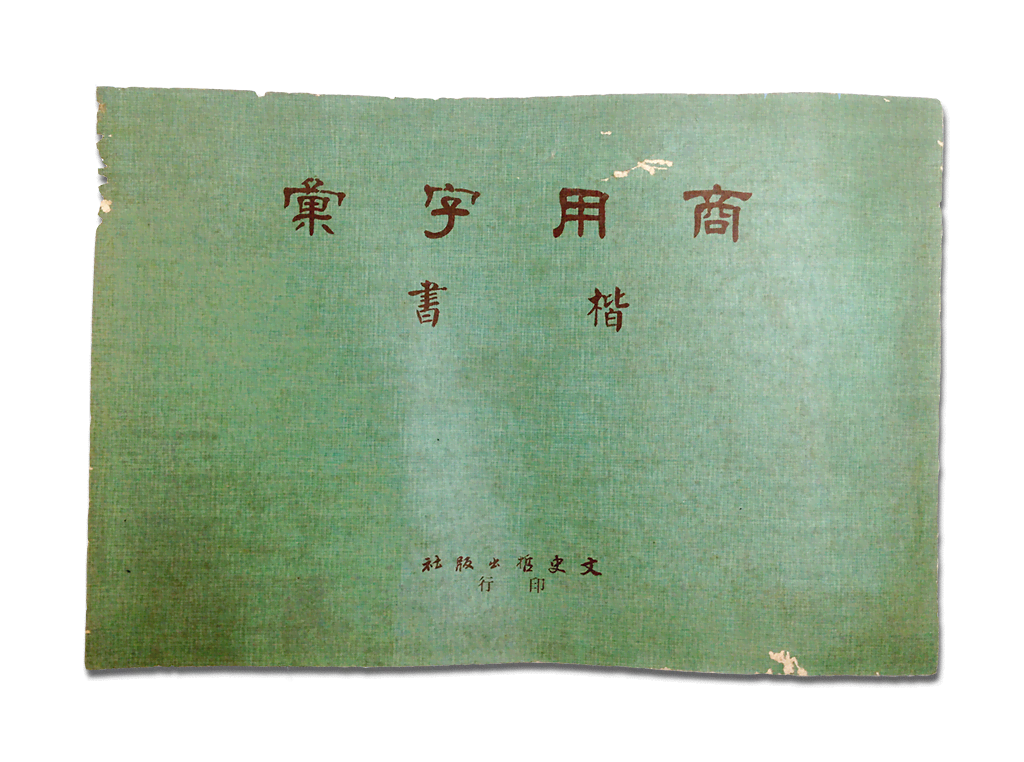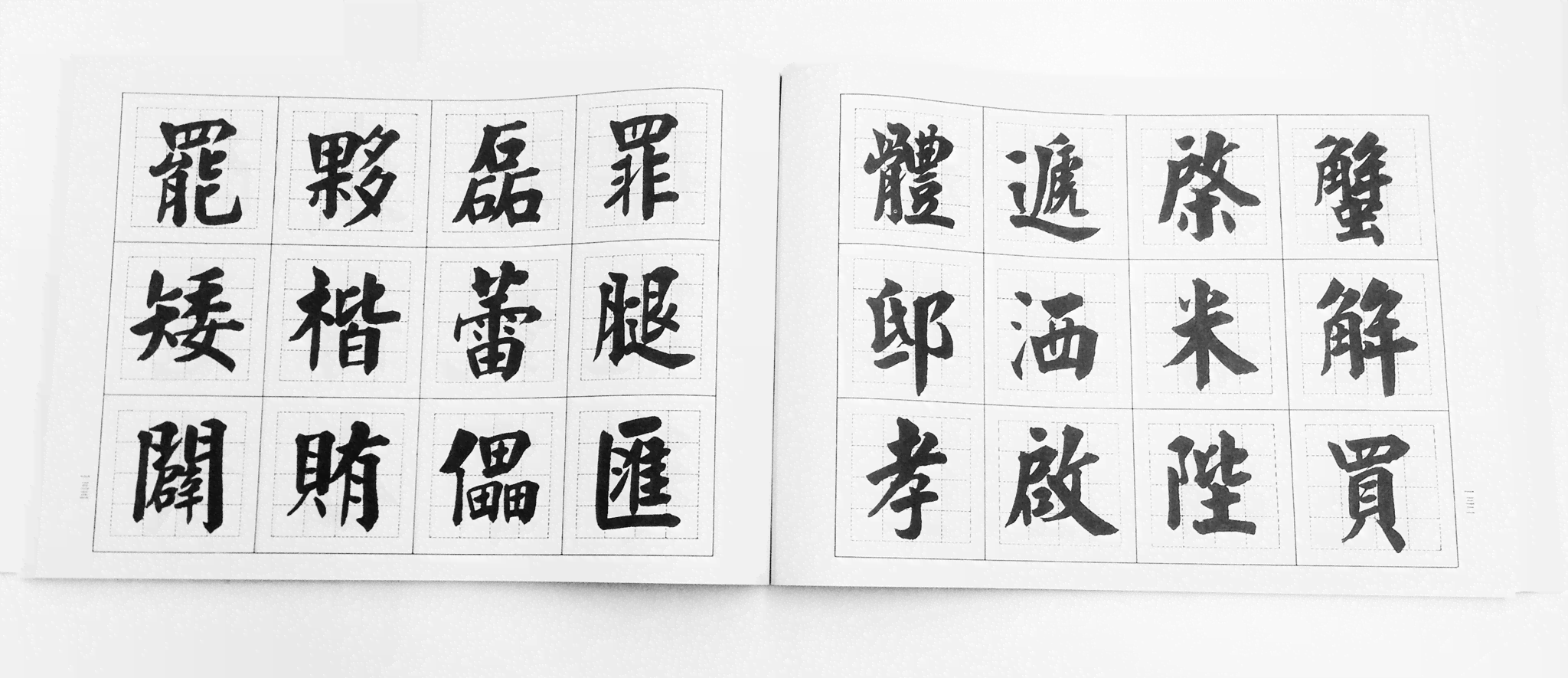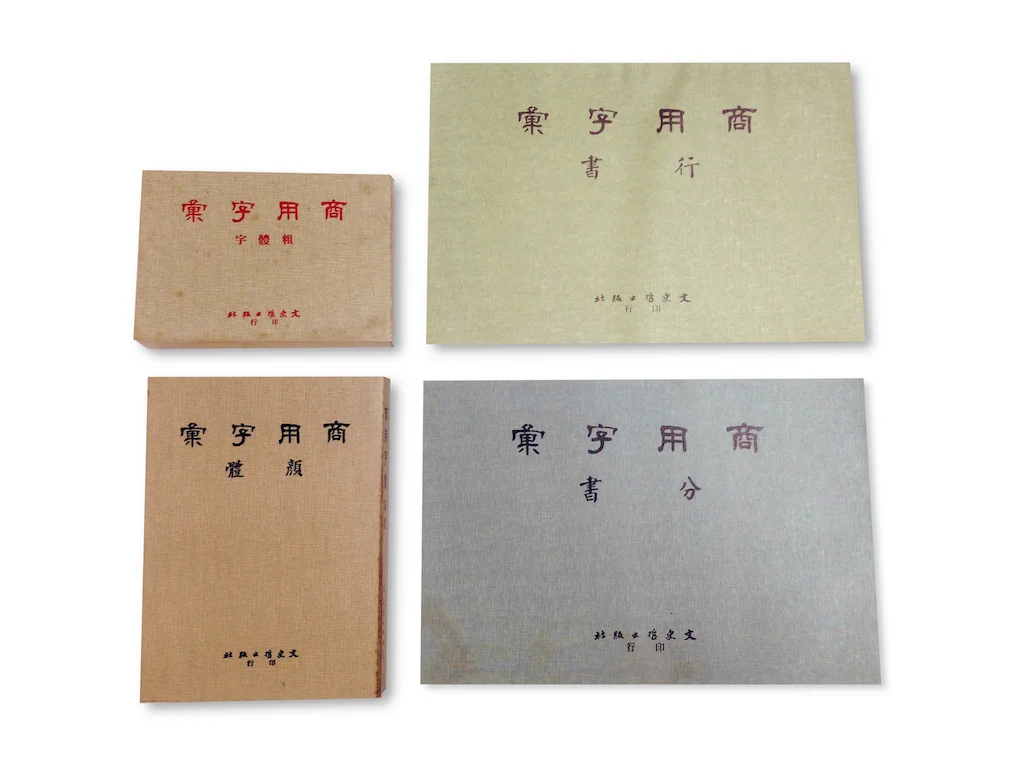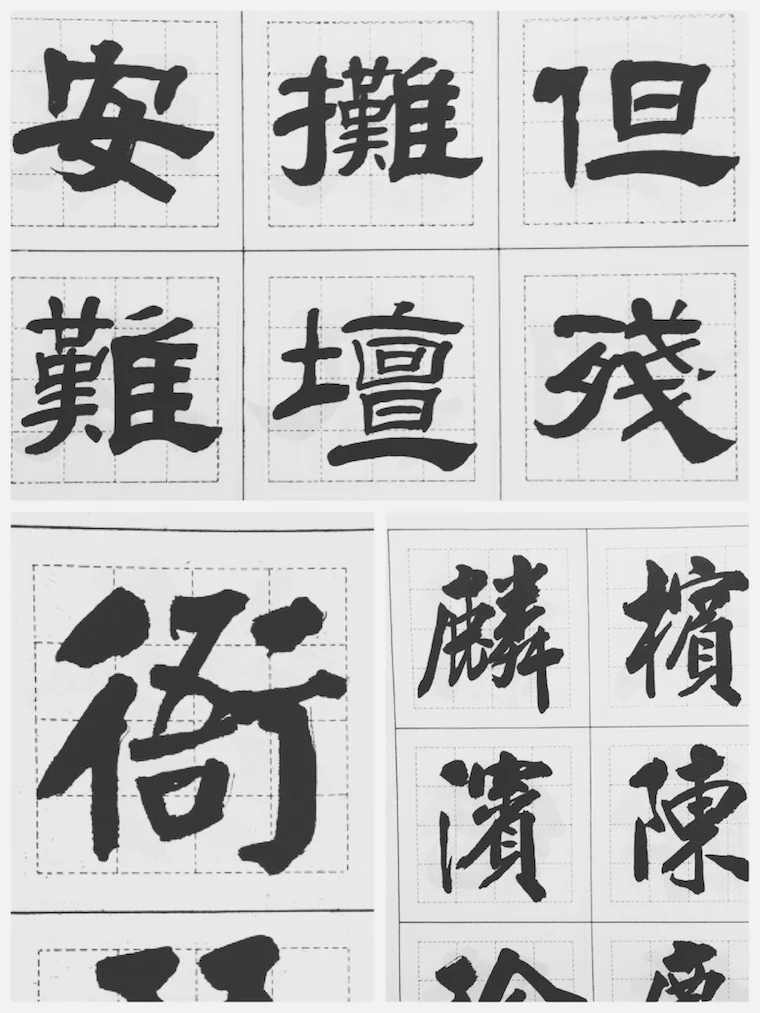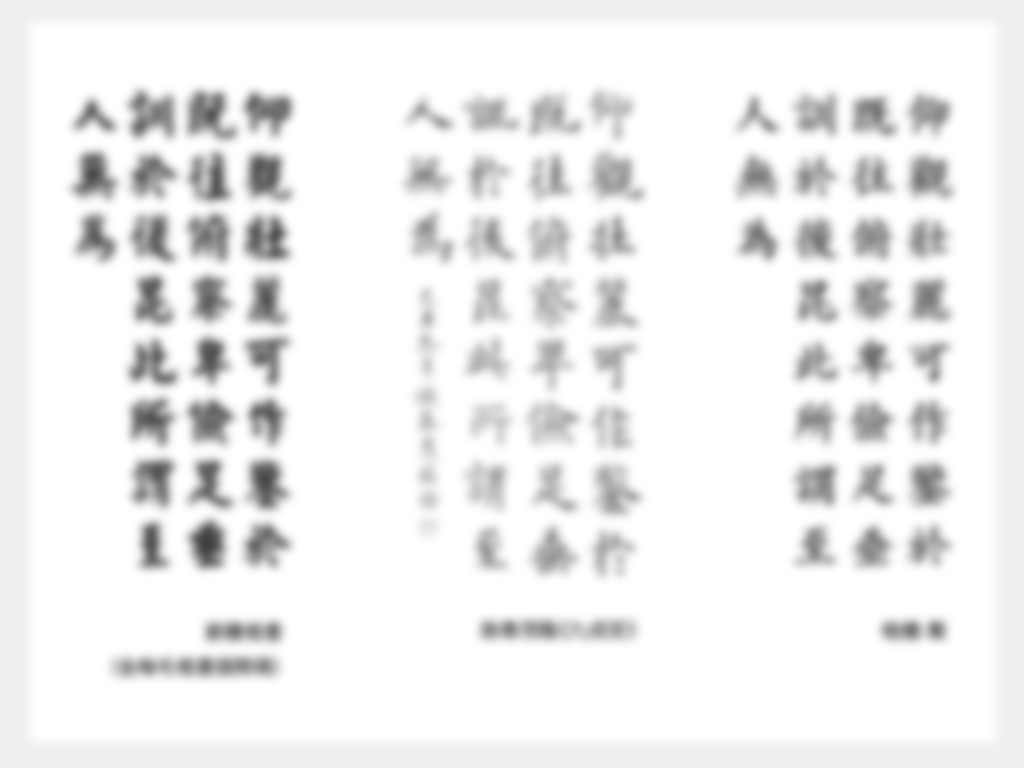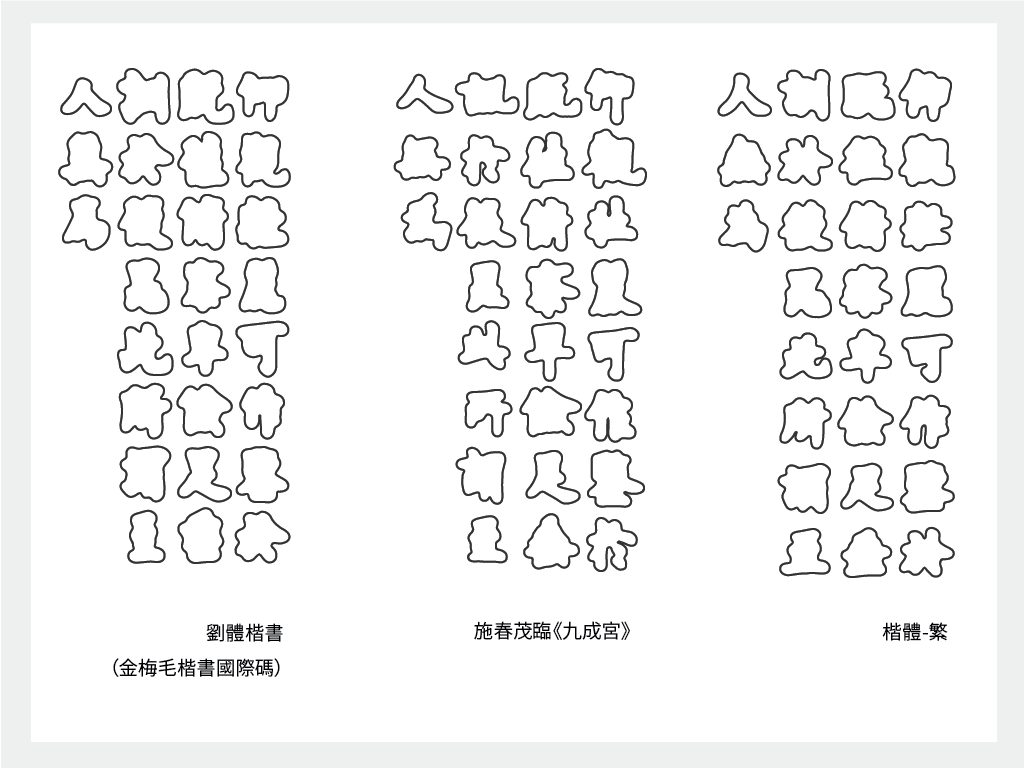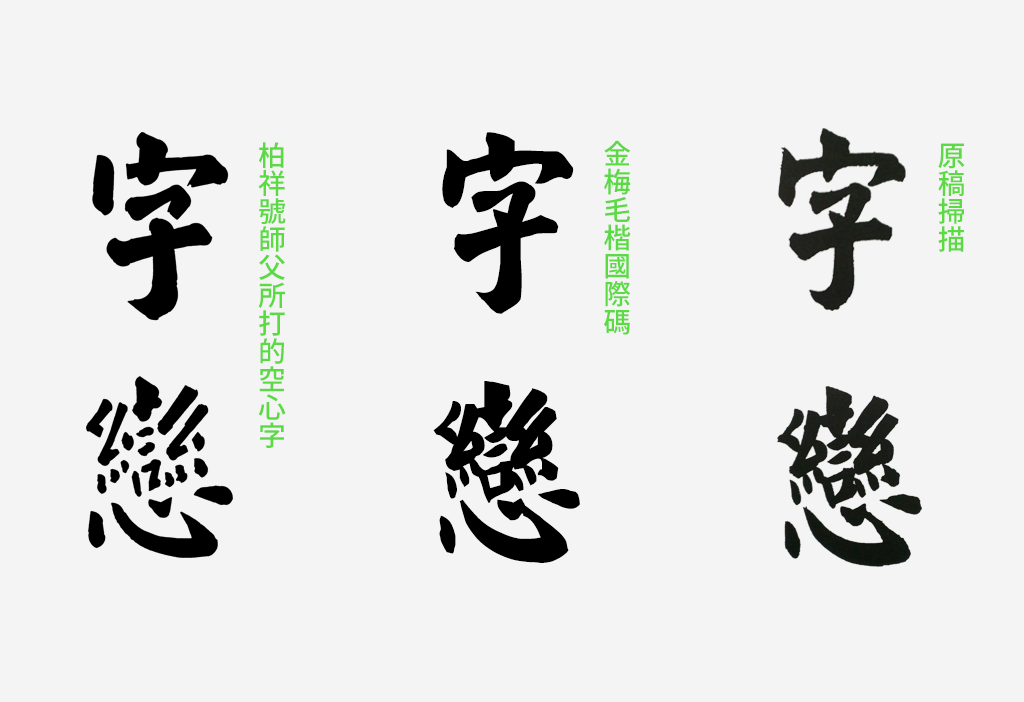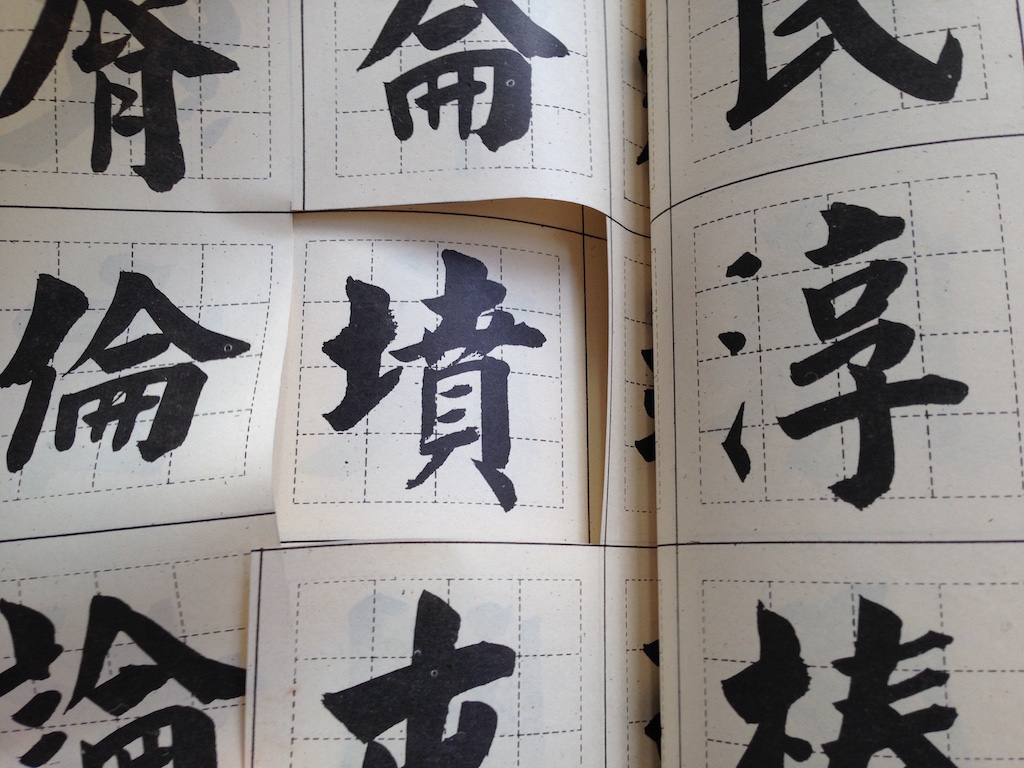
一早出門,門口停了台貨車,貨車上的水果紙箱都是這個字體。中午出去吃飯,小吃攤的招牌也是這個字體。下班後去看中醫,藥袋上也有。晚上去倒垃圾,垃圾車外殼又是它。去買宵夜,「鹽酥雞」八成也是這字體。順道去五金行買個水管,一瞥就知道是五金行。偶爾上街抗個議,警備車上也是這個字體。我們還可以一直舉例下去。
有人喜歡,有人不喜歡。但選台灣代表字型若只看使用率的話,《商用字彙》的楷書應該能高票當選。
不久以前,我們以為大致不脫文鼎、金梅或中國龍三家公司都曾出品的「毛楷」類字型。前年台北市長選舉時,神通廣大的鄉民還找到了「經典繁毛楷」做成文創商品。這些字型在骨架與筆形上太過神似,可能是互相「參考」來「參考」去的緣故,原著應已不可考。
直到有一天,我們在大稻埕專刻鐵皮空心中英文字的「柏祥號」發現一本書,把我們都嚇壞了。
本來就一直很好奇,為什麼打鐵出來的字長得都很像「毛楷」,莫非師傅也套字型去打?。想請師傅幫我們打「字嗨」一探究竟,結果師傅說他不會打「嗨」,原因是因為字帖上沒有。
什麼?師傅?你說什麼字帖來著?
台灣招牌字體來源之一:《商用字彙》
民國 71 年版《商用字彙》楷書篇內頁
那本字帖是《商用字彙》楷書篇。由文史哲出版社印行,年代是民國七十一年,也就是還沒有個人向量電腦字型的年代。原著為劉元祥先生。當下我們只知道這麼多而已,但翻著翻著,實在無法不驚呼:「天啊,找到了。」
文史哲出版社裡通常不會有人在那邊對著書本哇哇叫。顧店的總經理也有點摸不著頭緒,為什麼要買這麼久以前的招牌店字帖呢?但熱心的她一邊招呼著一邊說,這裡還有其他系列呢。
什麼啊啊啊啊竟然還有系列。
《商用字彙》不只有「楷書」篇,還有「顏體(顏真卿樣楷書)」、「分書(隸書)」、「行書」。一翻開,果真也是招牌上很常見的字體。沒想到竟然在這裡一網打盡,全是同一個人寫的。
如果你長期生活在台灣,一定對這些字體不陌生。
文史哲出版社彭正雄老闆說,這些字帖以前幾乎每家招牌店都有。這系列作品最早可以追溯到民國六十年代,也就是 1970—1980 之間。寫作者劉元祥先生自己先付梓,後來交給彭老闆的文史哲出版社印行再版。據彭老闆表示,這套書一本賣 500 元新台幣(當時一碗陽春麵是 1.5 元),共賣了 2000—3000 本左右。照這個規模推估,差不多大多數招牌店都買了吧。這還無法計算盜印版。據聞盜版一本 300 元,所以賣得更好。
關於商用字彙一書作者劉元祥先生
彭老闆想了一下,劉元祥先生大約在 2001 年左右就過世了,我們已無法獲得第一手消息。據《商用字彙》上的書籍資料,劉元祥是山東濰縣人,民國 13 年生(1924)。
曾經在台北市政府替長官寫書法(婚喪喜慶紅白帖、匾額、輓聯類)。也有許多熟門熟路的人會私底下求字於他。彭老闆因為印書的關係,看到書封上的字很喜歡,便透過印刷廠找到了劉元祥先生,為文史哲出版的書題字。聽到這裡,或許會以為他是位寫字匠,其實不然。
臺大歷史系的閻鴻中老師曾跟隨劉元祥先生學習書法三十餘年,憶起恩師,仍景仰萬分。劉元祥,字大鏞,禮貌上應該稱呼為劉大鏞先生。畢業於濟南師範學院,二次大戰時加入中國青年軍,隨國民黨政府來台後退伍。曾在中學任教,但與體制理念不合,遂不願再執教。偶然幫開招牌店的朋友寫字,意外成名,就漸漸以此為生計。
老古出版社印行的《佛門楹聯》由南懷瑾先生撰聯,書封上寫劉大鏞敬錄,閻鴻中老師認為較近於他的日常書寫。彭老闆也說,他著作署名是有區隔的。書法類作品留的是字「大鏞」,《商用楷書》登記著作權,所以留本名。
民國六十一年起,應南懷瑾先生之邀,劉大鏞在其「東西文化精華協會」教書法,前後有三年左右。這是他唯一一次開班授課。閻鴻中上課時只有十歲,但往後三十年,仍不時向劉元祥請益書法。回憶起老師,閻鴻中說,劉大鏞歷臨碑帖,相當熟悉古人底蘊,用功甚勤。然而他純為自娛,也是個人修養的方式。沒有辦過展覽,也沒有賣過字畫,實在是因為生活所需,才靠題字賺錢。當時,一段封面題字,可以收新台幣 10 塊錢。彭老闆與劉大鏞來往多次,遂成好友。劉先生索性不收錢了。
或許一方面是想流傳自己的作品,又想以此帶來一筆收入,所以劉元祥在民國 60 年代自己刊印了《商用字彙》套書。後來找上了彭老闆替他再版。彭老闆一口答應了。售價 500 元一本,300 元歸作者,200 元歸出版社。
劉大鏞先生上課時示範的筆跡。閻鴻中提供
關於台灣招牌字體:介在印刷字型與書法之間
不過,據閻鴻中表示,劉大鏞時常感慨無形中受到工作影響,書藝不能免俗,頗為遺憾。藝術家對自己的要求嚴格,是可以想像的。但既然業界採用率高,後來他也願意無償讓電腦字型業者使用,就當作是推廣書法藝術。或許因為如此,他的四套書法體才成為全台灣最常見的招牌字型。
有些書法老師可能一看到就嫌呆板,嫌搭配起來沒有書法應有的美,卻又同意這些字體適合招牌與印刷。甚至也不會否認,《商用字彙》系列其實是「商業設計」,或根本該說是「準字型」作品。
以《商用字彙》楷書而言,每個字都框在同樣的範圍裡、視覺上幾乎一樣大,這在書法上不必然是件好事。書法較講究變化,行氣參差,有飛舞的感覺。但這可能無法滿足大部分商家招牌的需求。這套字其實是以標題、看板文字角度出發「設計」的。跟做字型的原則很像,要考慮到排列組合,不能有些字特別突出,或有些特別小,要講究飽滿、顯目、易讀、而且預先假設到任何場合都能用。
從下圖的比較我們可以觀察到中間施春茂先生所臨的《九成宮醴泉銘》是結構形狀變化最明顯的。以一行行來看,會覺得比較有錯落起伏的感覺。書法裡的「行氣」就是這個意思。而字型化的劉體楷書,單字形狀變化較少,不過再比較右邊的「楷體-繁」(接近標楷體的電腦楷書字型),劉體楷書變化又更豐富了一些。
比較電腦化劉體楷書、書法《九成宮醴泉銘》以及 Mac 內建字型「楷體-繁」
模糊化後,比較三種字體的易認性。相較於「楷體-繁」,書法《九成宮》與劉體楷書都比較好辨認(然而,卻不一定像「楷體-繁」一樣平穩而好讀。
若把三種字體變成純粹的外框,會發現書法《九成宮》最形狀變化最靈活,有行氣。楷體-繁相較之下每個字的輪廓較為接近。而劉體楷書則介於中間。
台灣招牌字體的非戰之罪
雖然有書法的基因,不過還是會有人覺得劉體楷書失去了書法應有的氣息。尤其在許多卡典西德看板上(卡典西德是招牌割字最主要的材質),看起來甚至更僵化了。不過,字體要從紙本轉換到任何其他媒介上,都存在著鴻溝,不只是數位化會遇到這個問題。
就拿從前招牌店是如何運用《商業字彙》來說好了:透過簡單的設備,招牌店可以把字帖直接投影在看板上,依樣描繪;刻空心字的師傅用描圖紙也能複製字的輪廓。電腦字型版本則可能是原樣直接掃描再透過特定方式轉成貝茲曲線的。但是,投影法得到的是模糊的輪廓,描繪的師傅就像在玩著色書一樣,還是有很多需要自己填補跟詮釋的地方;刻空心字則是要打穿金屬板,也很難 100% 重現毛筆的筆觸。而大部分數位化後的劉體楷書,因為 auto-trace (自動描繪)設定不同,也不一定能完整表現原本豐富的細節。
光是比較線條邊緣細節的豐富程度,就會發現任何一種再現方式都是重新詮釋的
而這系列作品的影響力,正是一次次複製中所堆疊出來的。去到新加坡、柬埔寨,只要有華人街的地方,都能在招牌上看到他的字。但我們也得清楚一件事:絕大部分複製方式都難以 100% 原汁原味重現,《商用字彙》仍僅是「準字型」作品。總之,媒介的改變、數位化描繪的過程,都可能加入不同的詮釋。
FYI:當時的招牌店是怎麼做的呢?
先把要的字剪下來,才可以用來描邊或投影
彭老闆自己收藏了一台用於投影的機器,當時就要價 1500 元台幣。箱子裡面裝了一顆燈泡與兩塊鏡子,把字帖放在開口處,如此可以用來把字帖投射在一面鏡子上,如此再反射到另一面鏡子,最後投在要繪圖的表面上。
俗擱有力嗎?
對於台灣人來說,這種到處都是的楷書可能會散發一種獨特的土味,是「俗擱有力」界的翹楚,某種程度上能帶來信心:如果滷肉飯、排骨酥麵不用這字體,感覺就不好吃了。但想走高端路線的設計恐怕得視情況迴避這字體。這或許是非戰之罪。因為如上所述,要百分之百重現原味是很困難的。更別說市場現有的劉體楷書字型,絕大多數是在科技泡沫時代,為了搶市場,以粗糙製程掃描製作的字型,不乏失真、變形。翻著原稿,盡量相信自己的感受,型態上還是很美麗的。
不過,為了排除本地人美感疲乏的問題,我們也問了兩位熟悉漢字字體的非本地友人:大日本印刷的佐佐木小姐看了之後,她並不覺得俗氣,而且一看就覺得適合招牌用。勾筆較小這點,讓她感覺這字可能有學習顏真卿之處,但較顏體卻收緊很多;線條粗細對比大,富有個性,是具頗訴求力道的書風。而每字大小經過整理,也有計算衡量字腔間的餘白。可以看出與書法不同,是針對職業看板師傅的工作而設計的。
另一位友人,中國「字組」組長,書法家張彌迪也不覺得「俗」,反倒覺得很新鮮。彌迪非常喜歡他的字,而且認為原稿比字型保留更多、更流暢的書法味道,但又很統一協調。彌迪更提供了一種觀點:不仿把這類作品放到清末以來的「館閣體」脈絡中來看。《商用字彙》無論楷、行、隸筆法相對單調,但卻非常工整,這和民國初期的招牌字很接近。
出於黃自元之筆。清末以來文人的館閣體書法越來越規範化楷書的筆法,每個字的視覺大小趨於一致,而細節變化也減少,看起來相當工整。張彌迪提供。
不過他也提到,劉體楷書跟中國被濫用的「任政行書」有類似的境遇。被做成字型之後,到處濫用的結果讓大家無法平心靜氣地看待這套字體,都覺得很討厭──即便原稿尚稱雅俗共賞。俗不俗或許很主觀。覺得俗,可能有很多原因:浮濫、粗糙地複製上市,帶來了廉價感;它平常在生活裡如何被人對待,也可能影響我們的觀感。
最關鍵的可能還是我們如何對待這套字。《商用字彙》上的字體是否展現了書法之美,見仁見智:有人喜歡,有人不喜歡。但字型用戶有不同程度的數位與美學落差,我們不難看到一些比較不純熟的處理方式。例如招牌空間不夠,又想讓字大,就收窄起來,擠在一起;為了「有創意」,就使用一些很「跳」的配色,但沒有考慮到好讀與否。或是,任意地壓扁、壓瘦,又拿文字藝術師精美的漸層來伺候。電腦的便利或許讓許多人忘了對待文字是該給點尊嚴的。書法美的依據來自於手與毛筆互動所賦予的自然造型,哪裡該粗,哪裡該細,本就該如此。任意壓縮後的文字,整體比例就不合理了。不論再怎麼好的字,被這樣對待,也是不會美的。
有台灣味的書風
“「台灣味的街道風情,也許就是看到劉體楷書所製作出的『請勿◯◯』之類的割板字體所展現出來的。台灣味可說是這種書風。東京沒有像這樣的文字,感到非常的羨慕。」
佐佐木愛”
佐佐木小姐這麼一補充,讓人開心之外又有一點慚愧。在台灣,很多人已經對這字體審美疲乏,甚至無視之,完全不知道在外地人眼光看來,竟能有獨特的審美價值。
近年來,社會對於美感的討論越來越踴躍。其中,不乏有人主張這個社會完全缺乏美感。問題或許不是如此。問題或許是:這個社會中美的事物很難以它最好的樣貌表現出來—這或許出於我們對自身環境所知太少,又貪圖方便、快速所致。劉體楷書正是這樣的例子。
攝於寧夏夜市。放眼望去,許多招牌的字體都源自於《商用字彙》。
後記
“「肉圓店招牌是一定要用這種楷書的。如果改用感覺時尚的細黑體,可能看起來就沒那麼好吃了。」
蘇煒翔”
我們去演講時曾經這麼提過(而且是真心的)。每天都見到,畢竟還是有感情在。可惜長期以來大量濫用下,自己的審美觀多少也被影響,無法認真的覺得它有什麼美的地方,總將它跟「俗」連想在一起。(相當失敬)
發現《商用字彙》後,總算讓我們見識到這個「台灣文字風景」的原貌,原來非常美麗。更令我們驚嘆的是,原來其他常見的那種行楷、顏體與隸書,都出自同一人的手筆:不只影響了台灣,甚至影響了東南亞、甚至全世界華人社區的街道景觀。在名家輩出如繁星浩瀚的書法史上,已經很難為劉大鏞先生標定一個獨特的位置。但不能否認的是,歷代眾多書法家中,也很少有人像他這樣,以非常特殊的方式影響了一個時代的文字風景。